Bild 1: Asemischer Text eines Teilnehmers
Bild 2: Voynich Manuskript
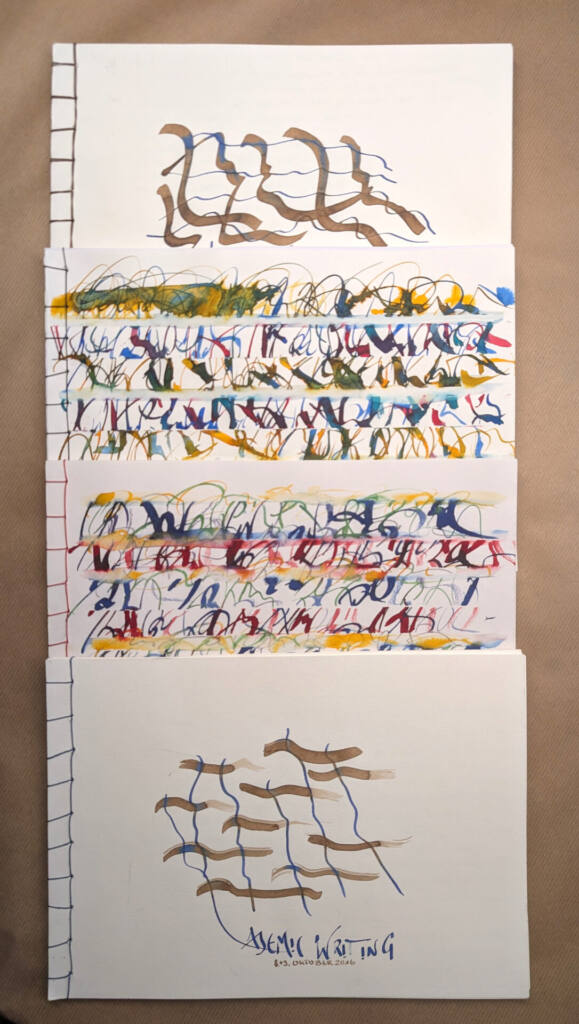
Bild 3: Ansichten der Kursbücher
Asemic Writing
Wir sind umgeben von Bildern und Schrift, lesbarer Schrift. Natürlich erfinden Texter schon einmal neue Worte, vor denen man erst einmal fragend steht: winterfest, Verhaarungscreme, Einkehrung, Ankerzentren usw. Ob sie eine Bedeutung haben, sinnvoll sind oder vielleicht sogar etwas verstecken wollen, sei dahingestellt. Immerhin kann man sie lesen, sie sind mit lesbaren Zeichen geschrieben und haben noch einen sprachlichen Bezug.
"Asemisches Schreiben" bezeichnet ein Schreiben ohne sprachlichen Bezug. Das Geschriebene ist entweder nicht lesbar oder beim Schreiben schon mit Absicht als nicht lesbar gestaltet. Eine asemische Handschrift verwendet keine bekannten Zeichen, oft ist es der Gestus, der Ausdruck, das Schriftbild, das in den Vordergrund rückt (siehe Bild 1). Das Handgeschriebene wird Ausdruck eines Gedankens, wird Bewegung, hat Dynamik und hält ein Geheimnis fest gleich einer Geheimschrift (Beispiele in den Bildern von Cy Twombly). Es gibt natürlich auch ein "asemisches Schreiben", das Zeichen benutzt, die dem Leser unbekannt sind und deswegen auch keine Bedeutung haben (siehe Bild 2 - eine Seite aus dem Voynich Manuskript, ein Buch, das bis heute nicht enträtselt (decodiert) ist.
"Asemisches Schreiben" bildet damit gerade den Gegensatz zu dem, was Schrift heute leisten muss: alles muss Bedeutung haben. Wir leben in einer Welt des Kodierens und Dekodierens von Nachrichten aller Art, die Inhalte werden zu Zeichenfolgen abstrahiert. Meist auch noch durch Einsatz von Maschinen. Mit Asemic Writing lösen wir uns von der Funktionalität und Zweckmäßigkeit.
In diesem Kurs werden wir uns dem "Asemischen Schreiben" in zwei Richtungen nähern: von einem lesbaren Text zu einem gestischen Ausdruck kommen, in dem das Schriftbild die inhaltliche Bedeutung aufnimmt und in einen handschriftlichen Gestus überleitet (ähnlich dem Bild 1). Die zweite Richtung folgt eher dem Bild 2. Es wird eine Collage aus einem Bild und einem asemischen Text bestehen, der mit unbekannten Zeichen geschrieben den Inhalt oder das Dargestellte beschreibt.
Entwicklung und Verwendung des Asemic Writing
"Asemic Writing / Asemischem Schreiben" ist traditionell "unlesbar". 1997 verwendeten die visuell arbeitenden Poeten Tim Gaze und Jim Leftwich das Wort asemic, um ihre quasi-kalligrafischen Schreibgesten zu benennen.
Sie begannen dann, sie sowohl online als auch gedruckt an Poesiezeitschriften zu verteilen. Die Autoren untersuchten sub-verbale und sub-letterale Formen des Schreibens und textliche Asemie als eine kreative Option. Seit den späten 1990er Jahren hat sich Asemic Writing zu einer weltweiten literarisch-künstlerischen Bewegung gemausert. Sie ist besonders in der ersten Hälfte des 21. Jahrhunderts gewachsen, obwohl es bereits eine lange und komplexe Geschichte gibt, die den gegenwärtigen Aktivitäten vorangeht. Hier ist besonders die abstrakte Kalligraphie in der Form des wortlosen Schreibens zu nennen.
Asemic Writing tritt in der avantgardistischen Literatur und Kunst mit starken Wurzeln in den frühesten Formen des Schreibens auf. Die Geschichte der heutigen Asemic Bewegung geht auf zwei chinesische Kalligraphen zurück: den "verrückten" Zhang Xu, einen Kalligraph der Tang-Dynastie (um 800), der berühmt für seine unleserliche Kalligrafie war, und den jüngeren "betrunkenen" Mönch Huaisu, der sich auch mit unleserlicher Kursivschrift auszeichnete Kalligraphie. Später erweiterten japanische Kalligraphen den chinesischen abstrakten kalligraphischen Ausdruck durch Hitsizendō (den Weg des Zen durch den Pinsel), so dass ihre Werke die formale Präsentation hinter sich lassen und "mit der Vitalität der ewigen Erfahrung atmen".
In den 1920er Jahren schuf Man Ray, der von Dada beeinflusst war, mit seinem Gedicht Paris, Mai 1924, ein frühes Werk des wortlosen Schreibens, das nichts weiter ist als Striche auf einer Seite. Später in den 1920er Jahren begann Henri Michaux, der von asiatischer Kalligraphie, Surrealismus und Automatic Writing beeinflusst wurde, wortlose Werke wie Alphabet (1925) und Narration (1927) zu schaffen. Michaux bezeichnete seine kalligrafischen Arbeiten als "innere Gesten". Der Schriftsteller und Künstler Wassily Kandinsky war ein früher Vorläufer der asemischen Schrift, wobei sein lineares Stück Indian Story (1931) eine vollständige textuelle Abstraktion darstellt. In den 1950er Jahren gab es Brion Gysin (dessen Kalligrafie von arabischer und japanischer Kalligrafie beeinflusst wurde), Isidore Isou (der Lettrisme gründete), Cy Twombly (ehemaliger Cryptologe der US Army) und Morita Shiryū / Bokujin-kai Group (Ink Human Society) alle erweiterten das Schreiben in unleserliche, abstrakte und wortlose visuelle Markenzeichen.
Ohne Worte zu sein, sagt nichts und sagt alles.